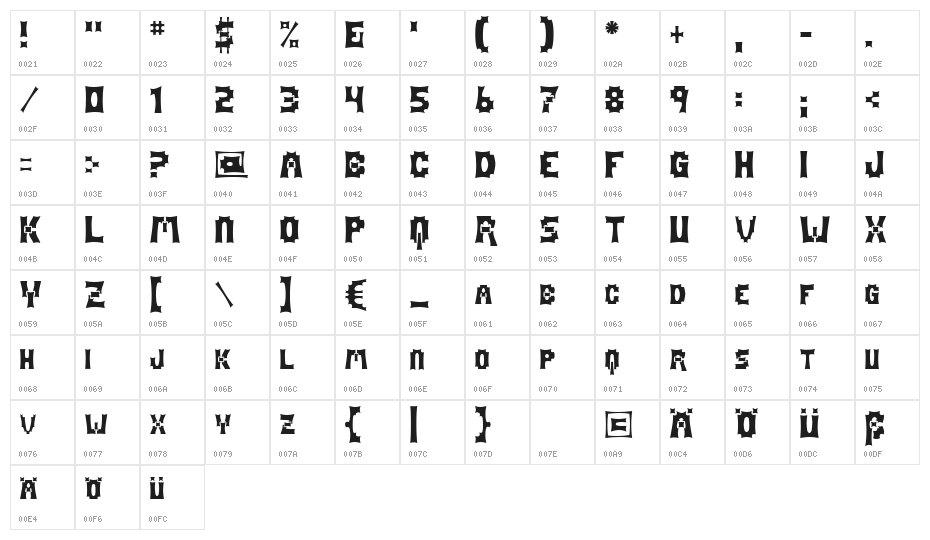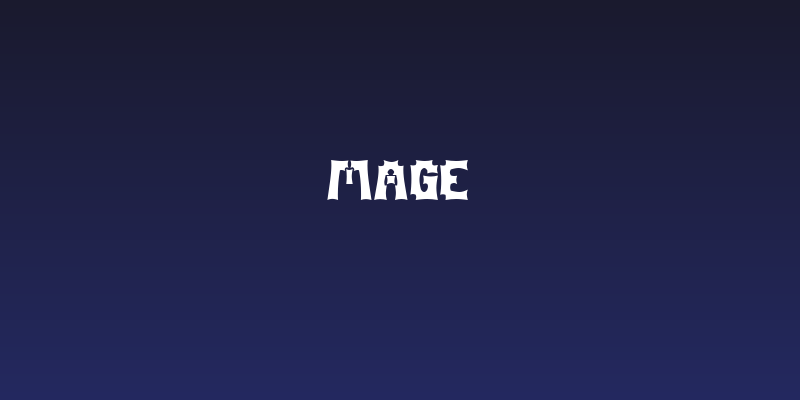
Mage Font
| Stil general | Gothic, Decorative |
| Proiecte propuse | Ideal for posters, album covers, Halloween-themed designs, and any project requiring a dramatic, gothic touch. |